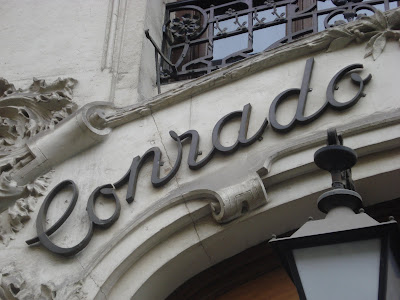
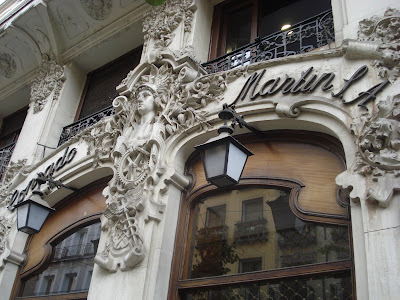
En la calle Mayor, números 16 y 18.
Sobre un edificio ya existente se acomete una reforma de la fachada en 1908 a cargo de los hermanos J. Pedro y Miguel Mathet para la compañía comercial Conrado Martín SA.
La reforma, que ganó un premio del Ayuntamiento ese mismo año, se realiza en estilo Art Nouveau mientras que para el rótulo del establecimiento se opta por una tipografía manuscrita o caligráfica.
Aunque actualmente esté pasada de moda, durante mucho tiempo se ha considerado que este tipo de letra inspiraba valores seguros como respetabilidad y confianza.
Las cursivas inglesas proceden de la escritura común con pluma de acero, y nacen oficialmente un día del año 1700 cuando el rey Jorge IV de Inglaterra solicita al fundidor francés Firmín Didot una letra que imite la inglesa manuscrita.
La Mistral quizá sea la más representativa de esta familia de letra inglesa.